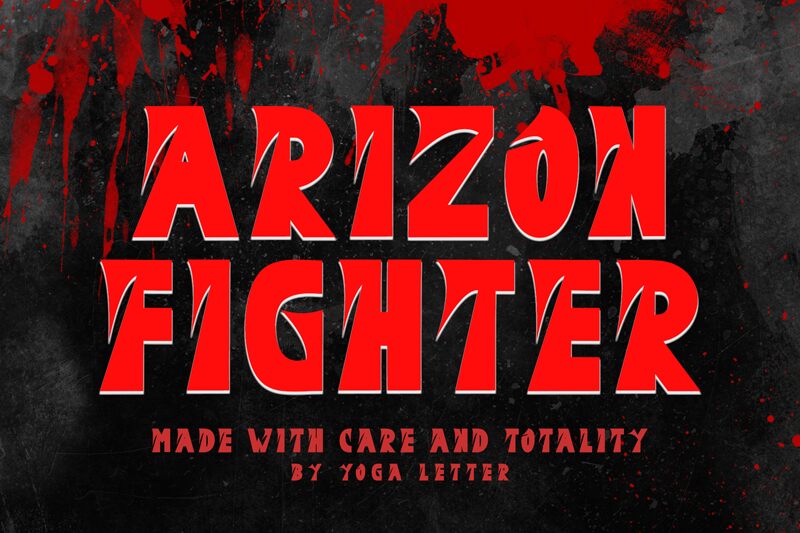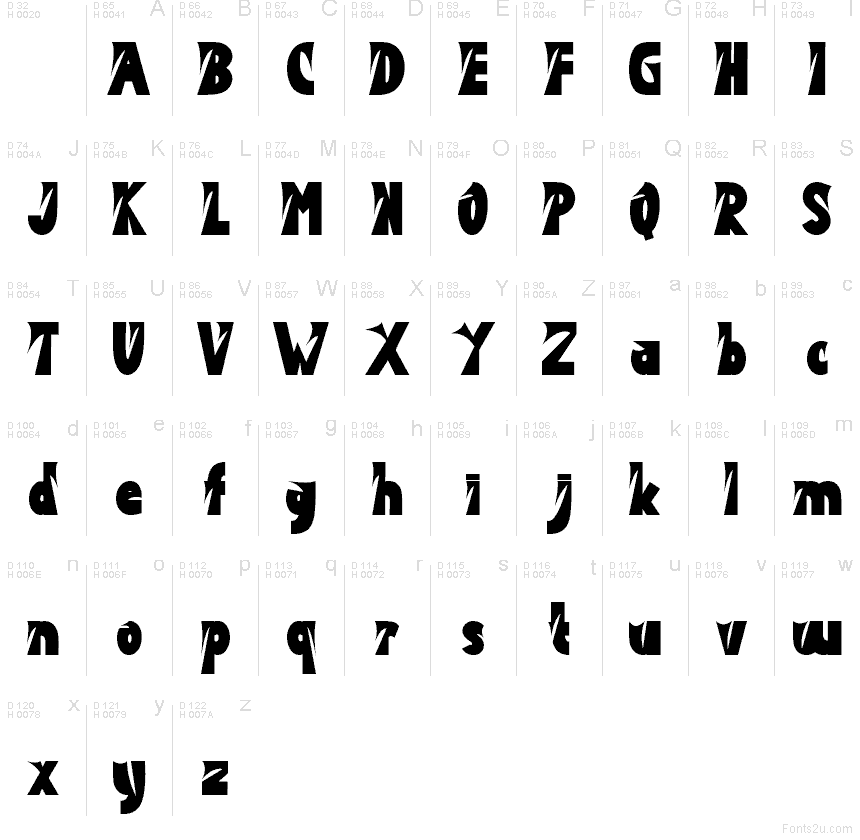
Arizon Fighter Demo
Arizon Fighter de Yoga Letter es una tipografía display gratuita con un estilo cómico y distorsionado. Sus letras combinan formas inclinadas y redondeadas con cortes afilados y bordes irregulares, creando un ritmo visual rugoso y artesanal en lugar de un acabado pulido.
Arizon Fighter funciona de maravilla en titulares de pósteres, menús de juegos, portadas de álbumes, folletos de eventos y diseños de moda urbana que buscan ese toque gráfico rebelde. Sus curvas quebradas y uniones angulares le otorgan un carácter fuerte y hecho a mano, sin perder la compactibilidad de cada palabra.